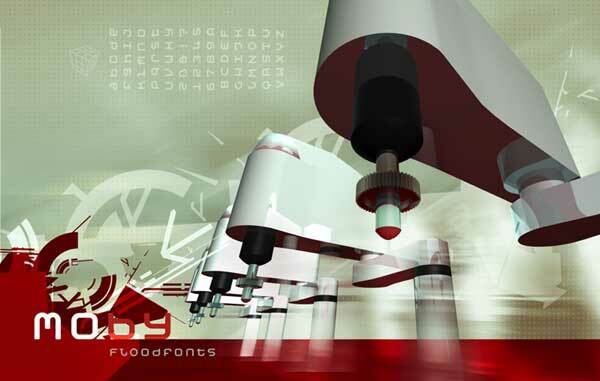
Moby Bold 字体
Moby 字体家族,包含 2 款字体
Felix Braden 设计的 Moby Bold 是一款免费标题字体,拥有圆润的块状结构和方形字腔,呈现出稳固且具有工业感的造型,没有任何尖锐边缘。粗重的轮廓和柔和的转角使字形显得紧凑且令人印象深刻,特别是在短单词中,重复的圆形几何造型能够起到极佳的视觉效果。
Moby Bold 非常适合用于标志设计、海报标题、专辑封面、包装和标识,因为其粗壮且简化的造型让人一目了然。这款免费字体也非常适合体育品牌形象和简短的网页标题,其流畅的切口和坚固的字形无需额外装饰,即可带来强烈的视觉冲击力。